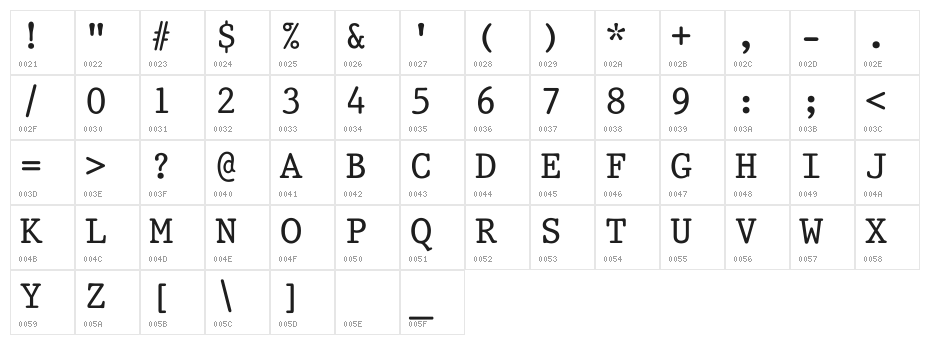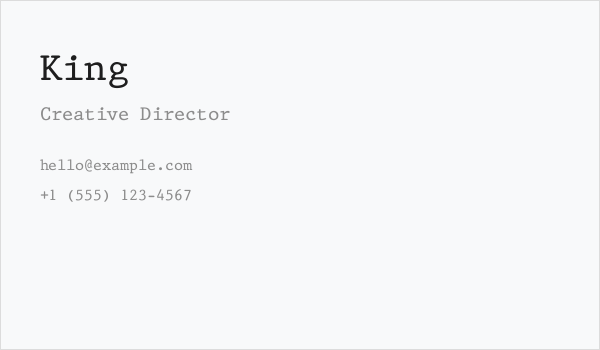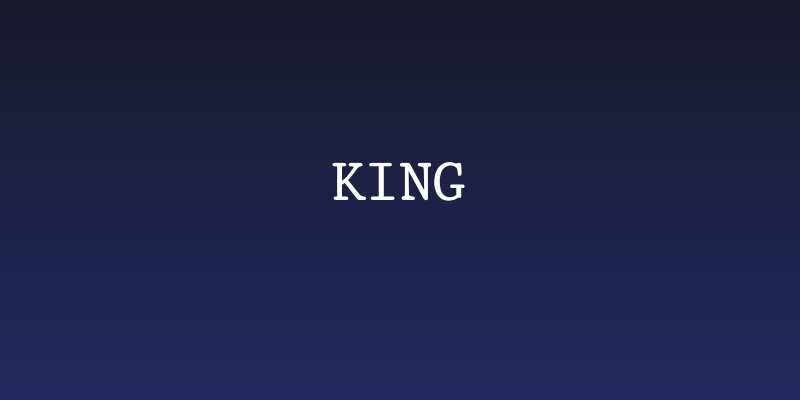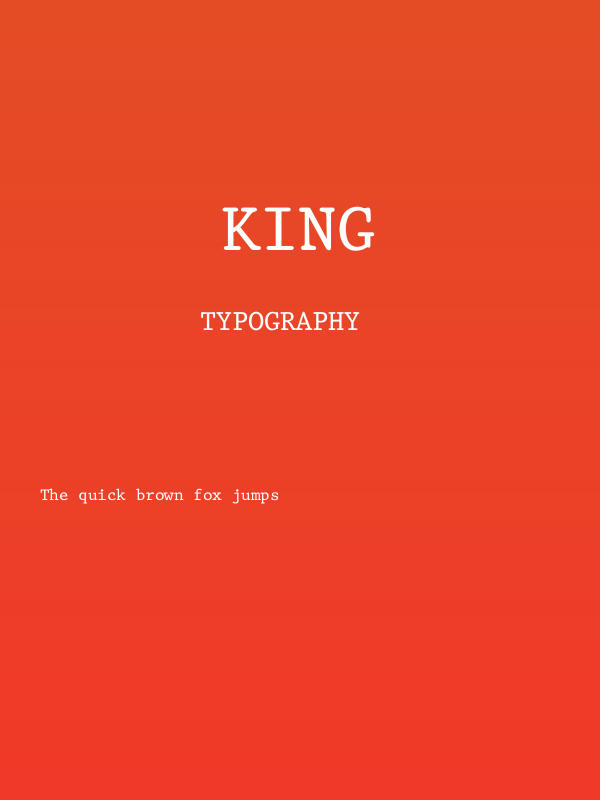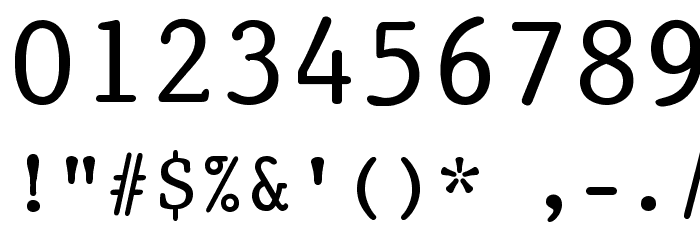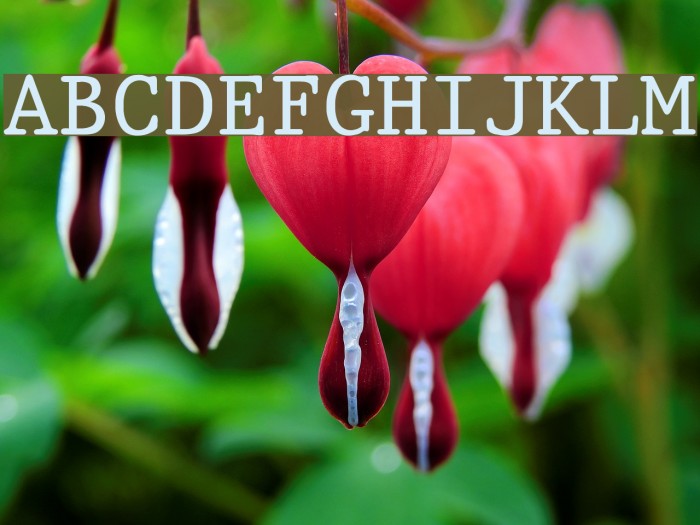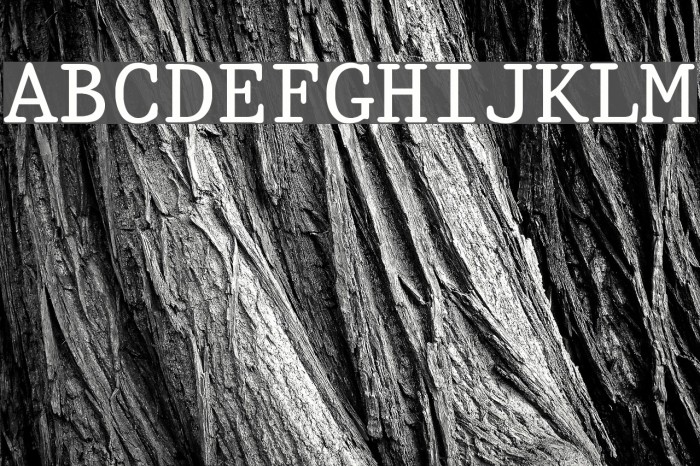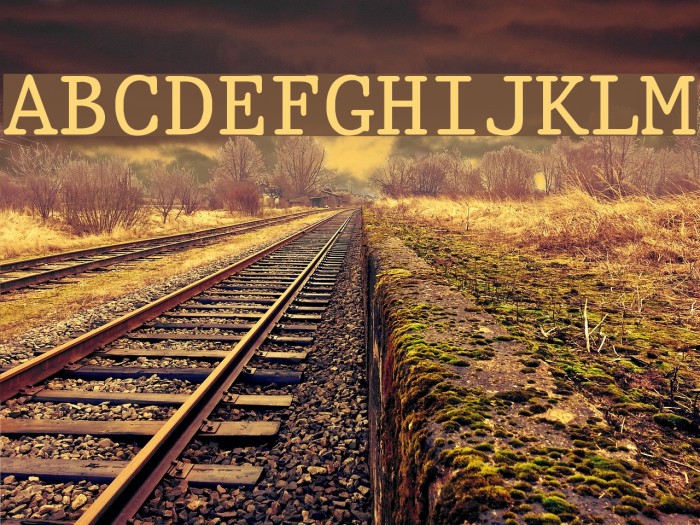
King Font
✎ Typewriter
| Kategorien | Typewriter |
| Gesamtstil | Classic |
| Anwendungsfall | Headlines, Body text, Logos |
| Vorgeschlagene Projekte | Ideal for editorial design, book covers, formal invitations, and branding materials. |